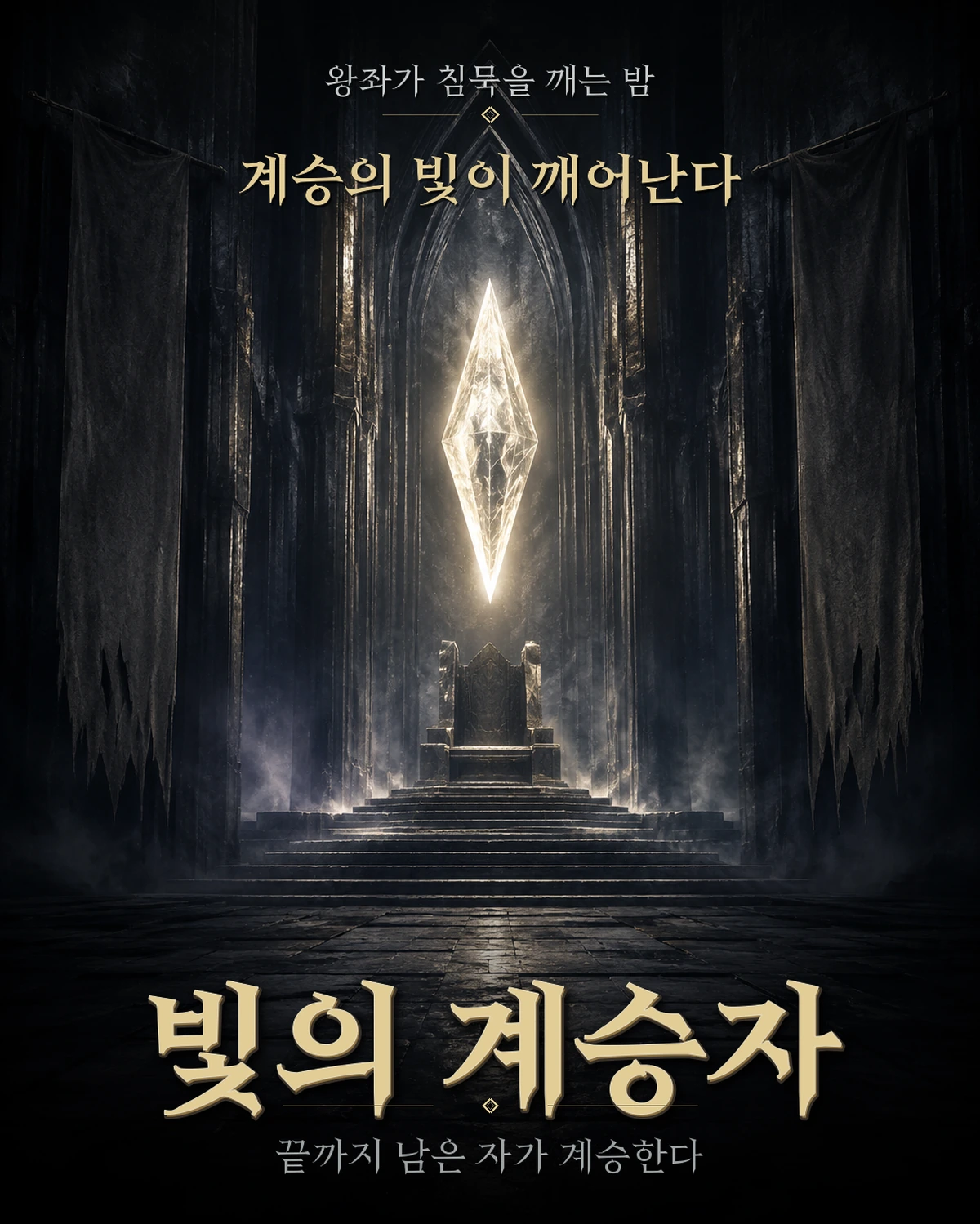
빛의계승자 — 펀플로X산돌에서 배포하는 무료 폰트입니다. 판타지 세계관의 신비로운 분위기와 다이아몬드 형태의 장식이 돋보이는 세리프체
게임 빛의계승자를 위해 펀플로와 산돌커뮤니케이션이 함께 만든 서체입니다. 지적재산권도 두 회사가 함께 갖고 있습니다.
모티브를 게임 세계관에서 곧장 가져왔습니다. 판타지 게임의 부서진 검기와 찢어진 파편을 날카로운 세리프로 옮겼고, 화려하고 고풍스러운 그래픽과 빛을 상징하는 은유를 디자인 요소로 표현했다고 설명합니다. 획 끝의 뾰족한 세리프가 그 결과물입니다.
굵기는 Regular와 Bold 두 가지입니다. 판타지나 게임 콘텐츠의 타이틀, SNS 카드처럼 분위기가 맞는 자리에 어울리고 본문에는 맞지 않습니다. 라이선스에 특이한 조항이 있습니다. 무료로 상업적으로 쓸 수 있지만 폰트를 수정하거나 재배포하는 것, 그리고 **콘솔과 PC, 모바일 게임에 폰트를 탑재하는 것은 권리자의 서면 동의가 있어야 합니다.** 게임 서체인데 게임에 넣으려면 따로 허락을 받아야 하는 셈이니, 게임 개발에 쓰실 계획이라면 미리 문의하세요.